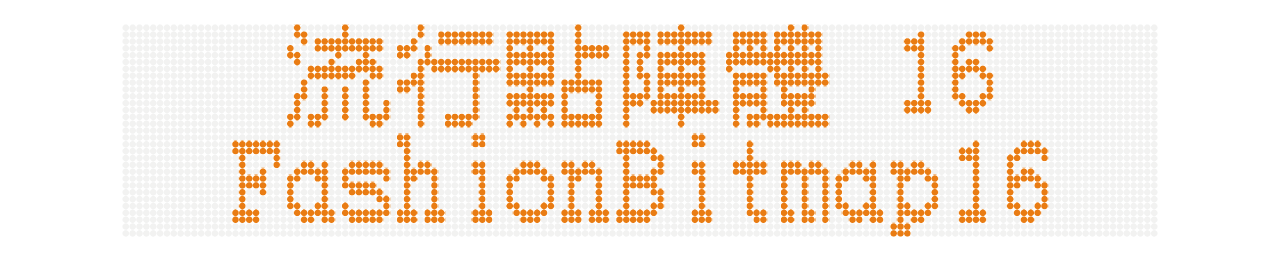
《流行点阵体 16 (FashionBitmap16)》是一款基于 KH 字体系列的改进版字体,旨在更适合在繁体中文环境中使用。我们对一些标点符号进行了调整,加入了一些日本常用的书写方式,同时增加了一些字符,使得该字体使用起来更加方便!
这是一种具有非常強烈艺术风格的字体,非常适合用于像素画、游戏相关主题等领域。